Открытые и закрытые формы букв: «а», «е», «с» и варианты
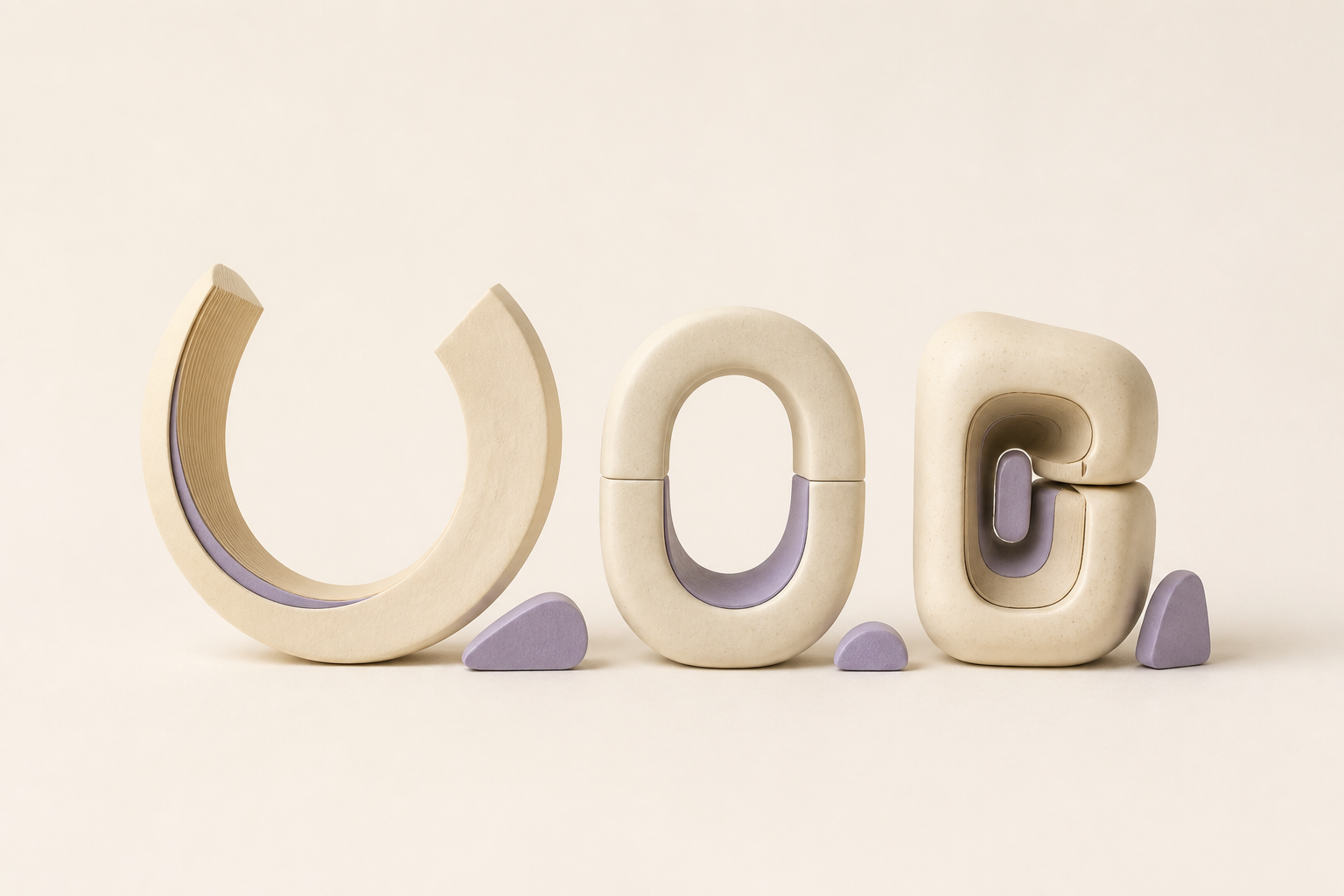
Открытые и закрытые формы букв: главное за минуту
Открытые и закрытые формы букв отличаются тем, насколько свободно внутреннее пространство знака сообщается с окружающим полем. У «с» и «е» это прежде всего ширина апертуры, у «а» — характер внутренней конструкции и просвета. Ниже разберём варианты букв, их влияние на читаемость и применение в шрифтовом дизайне.
Что означают открытые и закрытые формы в типографике
Открытая форма — это конструкция, в которой внутренний просвет буквы имеет заметный выход наружу. Самый очевидный пример — «с»: её дуга не замыкается, а пространство внутри чаши открыто с одной стороны. Закрытая форма образует более замкнутый силуэт, поэтому внутренний просвет воспринимается как отдельная область внутри знака.
В шрифтовом дизайне важно различать апертуру и внутренний просвет. Апертура — место раскрытия формы, через которое внутреннее пространство визуально соединяется с внешним. Просвет — свободная область внутри или рядом со штрихами. На восприятие влияют оба параметра, а также толщина штрихов, контраст, ширина знака, положение оси и размер набора.
Почему открытость влияет на читаемость
При малом кегле тонкие детали букв частично теряются: пиксельный экран, печать на рыхлой бумаге или недостаточный контраст уменьшают различия между штрихами и просветами. Более открытая апертура сохраняет узнаваемый силуэт, тогда как слишком закрытая форма может стать визуально плотной. Поэтому открытые конструкции часто встречаются в интерфейсных и текстовых шрифтах, где важны быстрое распознавание и устойчивость к плохим условиям отображения.
Почему термин нельзя применять механически
Открытость не измеряется одной универсальной границей. Два шрифта могут иметь одинаково незамкнутую «с», но ощущаться по-разному из-за ширины апертуры, формы терминалов и контраста. Кроме того, «а» обычно описывают через одноэтажную и двухэтажную конструкцию, а не просто как открытую или закрытую. Корректный анализ учитывает всю систему знаков, а не один признак.
Буква «с»: открытая дуга и размер апертуры
Буква «с» — самый наглядный пример открытой формы. Её основной элемент напоминает дугу или чашу с разрывом справа. Если разрыв широкий, «с» выглядит воздушной и легко узнаётся в мелком тексте. Если концы дуги сближены, форма становится компактнее и темнее; при увеличении контраста она может приобретать более декоративный, плакатный характер.
Широкая и узкая «с» в разных сценариях
Для интерфейса, навигации и длинного текста обычно полезна умеренно открытая «с» с ясным направлением дуги. Она помогает быстро отличить знак от похожих округлых букв и не превращается в пятно после уменьшения. В заголовке, логотипе или короткой подписи можно позволить более узкую апертуру, если композиции нужна плотность. Но декоративность не должна разрушать узнаваемость кириллицы.
Практический пример: слово «свет» в двух начертаниях может иметь одинаковый размер и толщину, но разную ритмику. Открытая «с» оставляет больше белого пространства перед «в», поэтому начало слова кажется легче. Закрытая по ощущению «с» создаёт более тяжёлый вход в слово и может лучше работать в массивном заголовке, но хуже — в подписи мелкого интерфейсного элемента.
Буква «е»: раскрытие, глазок и внутренний баланс
В строчной «е» открытость связана не только с внешним разрывом, но и с небольшим внутренним пространством, которое часто называют глазком. Горизонтальный штрих пересекает чашу, а верхняя и нижняя части формируют характерный просвет. Если глазок слишком мал, «е» темнеет и начинает напоминать плотный овал. Если он чрезмерно велик, буква теряет цельность и выглядит рыхлой.
Как устроить «е» в текстовом шрифте
В текстовом начертании «е» должна сохранять различимый горизонтальный штрих и устойчивую чашу при уменьшении. Важно проверить её рядом с «с», «о», «а» и «в»: эти сочетания показывают, достаточно ли у буквы внутреннего воздуха и не выбивается ли она из общего ритма. В кириллическом наборе полезно также контролировать высоту знака, наклон терминалов и соответствие соседним буквам по оптическому весу.
В дисплейном шрифте дизайнер может сильнее подчеркнуть раскрытие «е»: сделать разрыв заметнее, изменить наклон окончания или увеличить контраст между чашей и горизонтальным штрихом. Такое решение хорошо работает в крупном заголовке, где форму рассматривают почти как графический объект. Для основного текста чрезмерно выразительная «е» быстро утомляет и нарушает равномерность строки.
Буква «а»: одноэтажная и двухэтажная конструкции
У буквы «а» есть два главных типографических варианта. Одноэтажная «а» строится проще: её силуэт напоминает округлую чашу со штрихом или хвостом. Двухэтажная «а» состоит из верхней небольшой формы и нижней чаши, соединённых вертикальным или наклонным элементом. Это не просто стилистическая замена: варианты создают разный темп чтения, разную плотность и разный эмоциональный тон.
Когда подходит одноэтажная «а»
Одноэтажная «а» часто воспринимается как более простая, дружелюбная и геометричная. Она естественно смотрится в логотипах, коротких заголовках, детских и технологичных интерфейсах, если остальные буквы поддерживают тот же характер. При выборе нужно проверить, не становится ли «а» похожей на «о» или «другой» знак из-за слишком маленького бокового элемента. В коротком слове такая ошибка заметна сразу.
Когда подходит двухэтажная «а»
Двухэтажная «а» обычно даёт более сложный силуэт и помогает разделять знаки в плотном тексте. Она уместна в книгах, статьях, новостных интерфейсах и других задачах, где важны привычность чтения и чёткая дифференциация букв. Её конструкция требует точной настройки: верхний элемент не должен сливаться с чашей, а внутренний просвет должен оставаться открытым после уменьшения и печати.
Как сравнивать «а», «е» и «с» в одном шрифте
Сравнивать формы нужно не изолированно, а в словах и связках. Важен общий оптический вес: округлые элементы «а», «е» и «с» должны выглядеть согласованно, даже если их геометрия различается. Полезно набрать несколько слов с повторяющимися структурами, уменьшить их до предполагаемого рабочего размера и проверить, какие просветы исчезают первыми.
Пошаговый выбор формы для конкретной задачи
Форма буквы должна следовать функции, а не моде. Один и тот же вариант может хорошо работать в логотипе и плохо — в интерфейсе. Чтобы принять решение, сначала определите размер, длину текста, среду отображения и желаемый голос бренда, а затем проверяйте не отдельный символ, а полноценный набор.
- Определите сценарий: основной текст, интерфейс, логотип, упаковка, плакат или экспериментальный дисплейный шрифт.
- Задайте рабочий диапазон размера и проверьте буквы в реальном масштабе, а не только в увеличенном редакторе.
- Выберите степень открытости «с» и «е», исходя из требуемой читаемости и плотности строки.
- Сравните одноэтажную и двухэтажную «а» в словах, где она соседствует с «о», «д», «е» и «с».
- Настройте толщину, терминалы, контраст и боковые поля после выбора конструкции, потому что они меняют восприятие просвета.
- Проверьте кириллические знаки в разных текстах и убедитесь, что стилистические решения не нарушают распознавание.
- Сделайте финальный тест на уменьшенном размере, в инверсии и в нескольких типичных сочетаниях символов.
Практические примеры применения
Интерфейс мобильного приложения
В кнопках и меню пользователь должен распознавать слова быстро, поэтому предпочтительны ясные просветы и умеренная открытость округлых знаков. Для подписи «Сохранить» важно, чтобы «с» не закрывалась визуально соседними буквами, а «а» не теряла характерный элемент. Слишком декоративная одноэтажная «а» может выглядеть привлекательно в заголовке, но снижать уверенность чтения в компактной навигации.
Логотип и короткий заголовок
В логотипе допустимо усилить индивидуальность: изменить раскрытие «с», сделать глазок «е» более графичным или выбрать одноэтажную «а» для цельного геометричного силуэта. Однако логотип часто воспроизводится в малом размере, поэтому после стилизации нужно проверить его в чёрно-белом виде, на светлом и тёмном фоне, а также без сглаживания. Уникальность формы не должна превращаться в угадывание текста.
Основной текст статьи или книги
Для длинного чтения важнее стабильный ритм, чем эффектность отдельной буквы. Открытая «с» помогает сохранить различимость в узкой колонке, хорошо настроенная «е» поддерживает равномерный серый цвет строки, а двухэтажная «а» добавляет сложный, но привычный силуэт. Решение следует оценивать на абзацах, списках, цифрах и знаках препинания, потому что шрифт работает как система.
Частые ошибки при работе с открытыми формами
- Считать любую незамкнутую букву автоматически более читаемой, не проверяя толщину и контраст.
- Копировать форму «а» из другого шрифта, не согласуя её с пропорциями «е», «с», «о» и «д».
- Оценивать знак только при крупном увеличении и не тестировать его в рабочем размере.
- Путать кириллические и латинские символы, особенно в логотипах, веб-шрифтах и смешанных текстах.
- Увеличивать апертуру настолько, что буква теряет плотность и начинает выпадать из общего ритма.
- Использовать декоративную конструкцию в длинном тексте, где она быстро утомляет и снижает скорость распознавания.
- Исправлять только контур, забывая о боковых полях, кернинге и соседних сочетаниях.
Чеклист проверки букв «а», «е» и «с»
Перед выпуском шрифта или макета пройдите короткий чеклист. Он помогает увидеть не только форму отдельного знака, но и её поведение в реальной типографической системе.
- Проверьте узнаваемость каждой буквы без увеличения.
- Сравните открытые и более закрытые варианты в одинаковом кегле.
- Наберите слова «свет», «мера», «каска», «адрес» и несколько собственных примеров.
- Оцените апертуру, глазок и внутренние просветы после растеризации.
- Проверьте прямое, курсивное, светлое и жирное начертания.
- Сопоставьте кириллицу с латиницей, если шрифт поддерживает оба алфавита.
- Убедитесь, что форма соответствует назначению и тону проекта.
Что такое открытая форма буквы?
Открытая форма — это конструкция с заметной апертурой, через которую внутреннее пространство знака сообщается с внешним полем. Наиболее очевидный пример — буква «с», но степень открытости можно обсуждать и у «е». Такая форма часто помогает сохранить различимость букв в мелком размере, хотя результат зависит от всей конструкции шрифта.
Чем закрытая форма отличается от открытой?
Закрытая форма воспринимается как более замкнутый и плотный силуэт: разрыв меньше, внутреннее пространство сильнее отделено от внешнего. Она может придать шрифту компактность и выразительность, особенно в крупных заголовках. Недостаток проявляется, если просветы становятся слишком малыми и буквы теряют ясность при уменьшении.
Какая «а» лучше: одноэтажная или двухэтажная?
Универсально лучшего варианта нет. Одноэтажная «а» часто подходит для дружелюбных, геометричных и коротких композиций, а двухэтажная «а» хорошо поддерживает плотный текст и привычную дифференциацию знаков. Выбор зависит от назначения, характера гарнитуры, размера и того, как буква выглядит рядом с «о», «е», «с» и «д».
Почему «е» иногда выглядит слишком тёмной?
«Е» темнеет, когда её глазок слишком мал, горизонтальный штрих слишком толстый или верхняя и нижняя части чаши сближены. Дополнительную плотность создают высокий контраст и тесные боковые поля. Исправлять проблему следует комплексно: проверить внутренний просвет, толщину штрихов, пропорции и сочетания с соседними округлыми буквами.
Как сделать букву «с» более читаемой?
Начните с проверки ширины апертуры и расстояния между концами дуги. Затем оцените толщину штриха, форму терминалов и общий контраст: большое раскрытие не спасёт знак, если он слишком тонкий или непропорциональный. Обязательно протестируйте «с» в словах, в мелком размере, в жирном начертании и рядом с «о» и «е».
Нужно ли делать одинаковые формы в кириллице и латинице?
Не обязательно. Кириллические и латинские «а», «е» и «с» являются разными символами, даже если визуально похожи, поэтому их можно строить с учётом особенностей каждого алфавита. При этом в едином шрифте они должны выглядеть родственными по пропорциям, оптическому весу, контрасту и характеру терминалов.
Вывод: форма должна работать на задачу
Открытые и закрытые формы букв — это инструмент управления читаемостью, плотностью и характером шрифта. У «с» ключевую роль играет апертура, у «е» — баланс раскрытия и глазка, у «а» — выбор одноэтажной или двухэтажной конструкции. Проверяйте буквы в словах, реальном размере и разных сценариях, а не только в окне редактора.